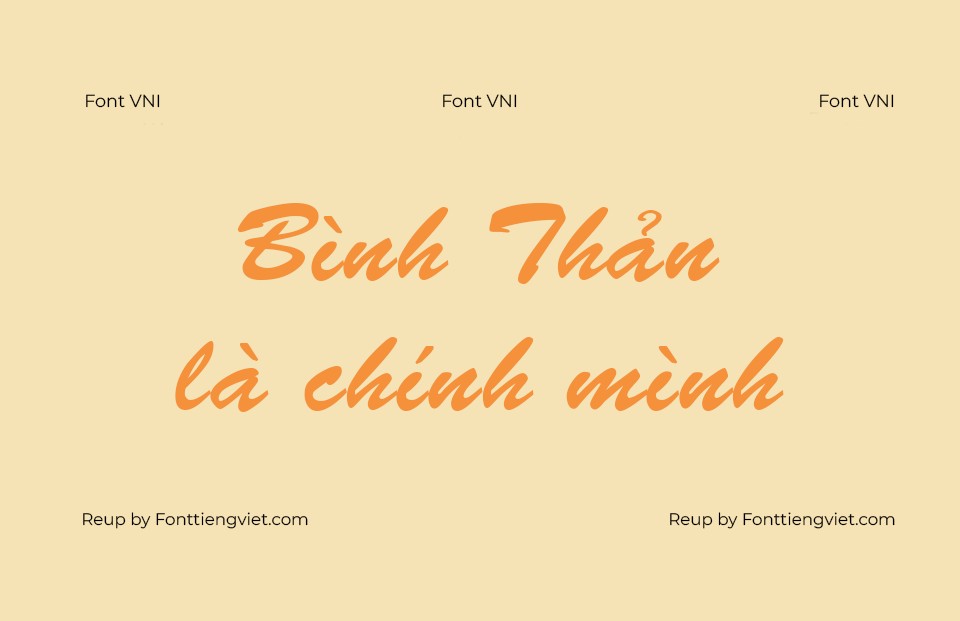
Font Việt hoá VNI Brush
Font Việt hoá VNI Brush – Lựa chọn hoàn hảo cho thiết kế nét cọ tự nhiên
Giới thiệu về Font Việt hoá VNI Brush
Trong thế giới thiết kế đồ họa hiện nay, việc tìm kiếm một bộ Font Miễn Phí có phong cách độc đáo luôn là ưu tiên hàng đầu của các bạn học sinh và thầy cô giáo. Font Việt hoá VNI Brush nổi bật với những đường nét mô phỏng nét cọ vẽ tay đầy phóng khoáng, mang lại sự mềm mại nhưng không kém phần mạnh mẽ cho tác phẩm. Đây là lựa chọn lý tưởng cho các biểu ngữ trường học, thiệp mời hoặc các dự án sáng tạo nghệ thuật đòi hỏi tính thẩm mỹ cao và sự gần gũi.
Ưu điểm nổi bật của bộ Font Việt hoá VNI Brush
Phong cách nghệ thuật ấn tượng
Đặc điểm nhận dạng của Font Việt hoá VNI Brush chính là những nét xước tự nhiên, tạo cảm giác như được vẽ trực tiếp bằng cọ mực. Điều này giúp các nội dung trình bày trở nên sinh động và có hồn hơn so với các font chữ truyền thống. Các em học sinh có thể dùng font này để làm báo tường hoặc trang trí bài thuyết trình thêm phần lôi cuốn.
Khả năng tương thích và dễ sử dụng
Kết luận và trải nghiệm Font Việt hoá VNI Brush